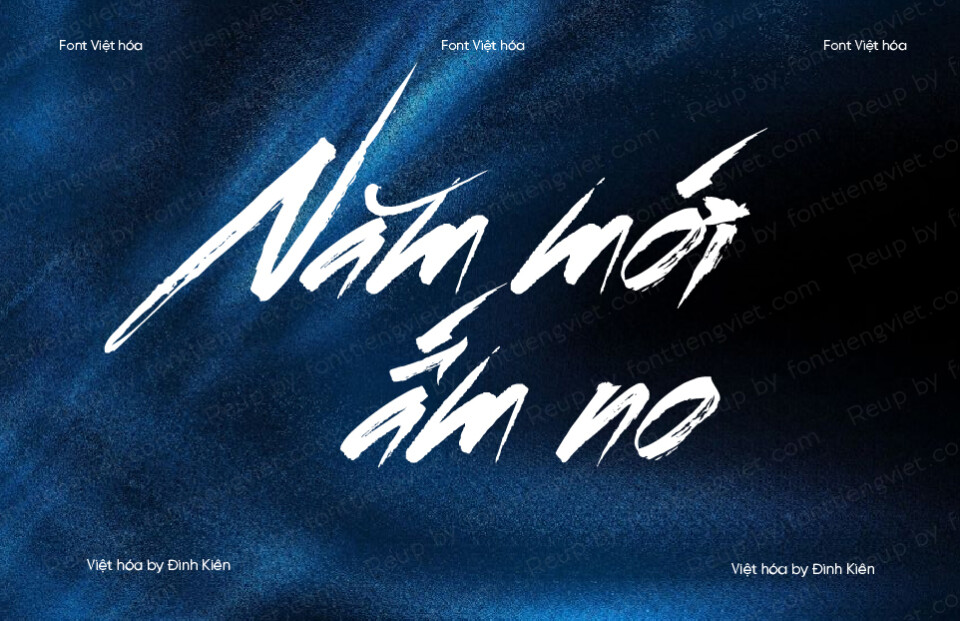
Giới thiệu về Font Việt hóa UTM But tre trong thiết kế
Trong lĩnh vực giáo dục và thiết kế học đường, việc lựa chọn một Font Chữ phù hợp đóng vai trò cực kỳ quan trọng. Font Việt hóa UTM But tre là một trong những bộ phông chữ viết tay độc đáo, mang phong cách thanh mảnh và mềm mại như nét bút tre truyền thống. Với các đường nét uốn lượn tự nhiên, bộ font này không chỉ giúp nội dung trở nên gần gũi mà còn tạo cảm giác thân thuộc đối với học sinh và giáo viên. Đây là lựa chọn lý tưởng cho các bài giảng điện tử, thiệp mời sự kiện trường học hoặc các bảng tin nội bộ cần sự nhẹ nhàng, tinh tế.
Đặc điểm nổi bật của Font Việt hóa UTM But tre
Bộ font này được tối ưu hóa hoàn toàn cho bảng mã Unicode, giúp người dùng gõ tiếng Việt có dấu một cách mượt mà mà không lo lỗi hiển thị. Sự kết hợp giữa nét thanh và nét đậm giúp Font Việt hóa UTM But tre giữ được vẻ đẹp chân thực như chữ viết tay trên giấy. Ngoài ra, tính tương thích cao với các phần mềm đồ họa như Photoshop hay Canva giúp các thầy cô dễ dàng tạo ra những tài liệu học tập sinh động và bắt mắt hơn bao giờ hết.
Cách ứng dụng Font Việt hóa UTM But tre hiệu quả nhất
Để phát huy tối đa vẻ đẹp của bộ font này, bạn nên sử dụng cho các tiêu đề ngắn hoặc các đoạn trích dẫn truyền cảm hứng. Tránh dùng font cho các văn bản dài vì độ uốn lượn có thể gây mỏi mắt. Khi kết hợp với các tông màu pastel hoặc nền giấy cũ, sản phẩm thiết kế của bạn sẽ mang đậm tính nghệ thuật và giá trị truyền thống Việt Nam. Hy vọng rằng bạn sẽ có những trải nghiệm sáng tạo tuyệt vời cùng Font Miễn Phí, Font Việt Hóa, Font Việt hóa UTM But tre để làm phong phú thêm kho tư liệu giảng dạy của mình.